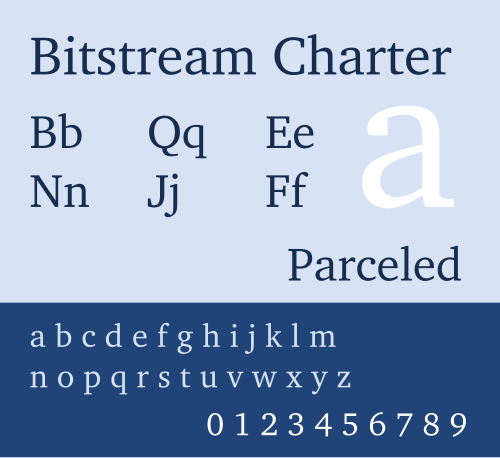
| カテゴリ | セリフ |
| 分類 | トランジショナルセリフ スラブセリフ |
| デザイナー | マシュー・カーター |
| 鋳造所 | ビットストリーム株式会社 |
| 作成日 | 1987 |
ビットストリーム・チャーターは、 1987年にマシュー・カーターがビットストリーム社のためにデザインしたセリフ書体です。 [2]チャーターは、18世紀に遡るピエール=シモン・フルニエの文字に基づいています。 [3]ビットストリームではトランジショナル・セリフ書体(ビットストリーム・トランジショナル801)に分類されていますが、スラブ・セリフ書体の特徴も備えており、そのように分類されることが多いです。[4] [5]
Charterはもともと1980年代の低解像度300dpiレーザープリンターでの印刷に最適化されており、その力強く読みやすいデザインにより、現代の高解像度レーザープリンターと安価な低解像度インクジェットプリンターの両方での印刷に適しています。その構造は、メモリの少ないコンピューターとプリンターに最適化されていました。2013年のインタビューで、Carterは「非常に簡素化された構造と最小限の曲線、より多くの直線セグメント...たとえばTimes New Romanと比較すると非常に経済的」であると説明しましたが、プリンターの急速な発展により、デザインを完成する前からこれは不要になったと指摘しました。[6]セリフ体の簡素化において、それはCarterの後の画期的なデザインであるMicrosoftのGeorgiaを予見していました。
1992年、BitstreamはCourierのバージョンとともにCharterのバージョンをXコンソーシアムに寄贈しました。この寄贈条件では、フォントの改変と再配布が許可されていました。これにより、Charis SILを含むBitstream Charterのオープンソース派生物が作成されました。[7]タイポグラファーのMatthew Butterickは、 Bitstream Charterを入手可能な最高の無料フォントの1つと考えています。[8]
その人気により、2004年にこの書体の新しいCharter Proリリースがリリースされ、追加の記号、数字(旧スタイル)、小文字の大文字を含む拡張文字セットが採用されました。[9]このバージョンは後にOS Xのシステムフォントとして追加されました。[要出典]
カーターは後にモノタイプ社からチャーターのサンセリフ体のリリースを検討するよう依頼されました。しかし、その試みが満足のいくものでなかったため、彼はそのアイデアを捨て、より過激で直接的な補完ではないデザイン、Carter Sans を採用しました。
歴史
憲章は、フォントサイズの標準化された測定システムである「ポイントシステム」を発明した18世紀フランスの活版印刷工、活字鋳造工、タイポグラフィ理論家であるピエール・シモン・フルニエの文字[3]に基づいています。